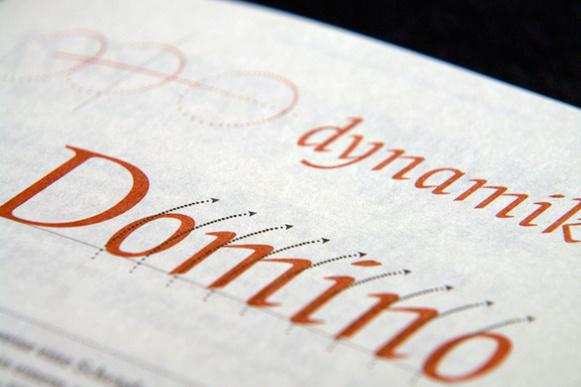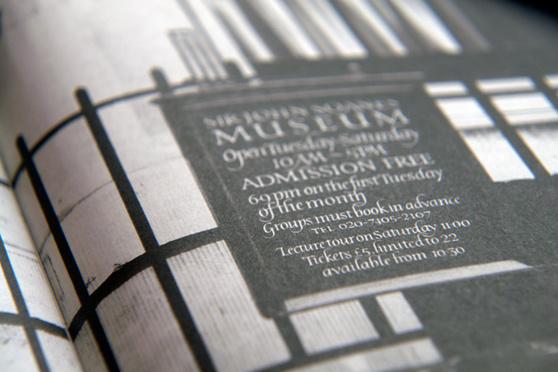
Die Typografie-Bücher aus dem »Niggli Verlag« sind nicht selten Abschlussarbeiten von Hochschulen. Einerseits ist es natürlich löblich, dass der Verlag Werke einer breiten Masse zugänglich macht, die sonst womöglich unbesehen in Universitätsarchiven verstauben würden. Andererseits macht ein erfolgreicher Abschluss nicht jede Arbeit gleichsam zu einem empfehlenswerten Buch. Als Beispiel sei hier das im letzten Jahr im gleichen Verlag erschienene Buch Bleiwüste genannt, das wohl offenbar ohne jegliche fachliche Korrektur in den Druck ging und entsprechend schlechte Bewertungen erhielt.
Insofern war ich auch bei dem neuen Buch »Kursiv – Was die Typografie auszeichnet« etwas skeptisch, denn auch hier handelt es sich wieder um eine Diplom-Abschlussarbeit, diesmal von Hendrik Weber an der Hochschule für Grafik und Buchkunst Leipzig.
Die zweifarbig gesetzte Broschur gefällt mir ihrer sachlichen und unaufdringlichen Gestaltung. Die angenehm lesbare Fließtextschrift Lirico geht ebenfalls auf das Konto des Autors.
Das Buch gliedert sich in drei Teile. In der Einleitung geht der Autor dem Zweck und der Definition des Begriffes auf den Grund. Denn so gewöhnlich uns der Begriff auch erscheint, so schwierig gestaltet es sich doch, ihn exakt zu definieren. Der zweite und größte Teil des Buches widmet sich der Geschichte der kursiven Schrift. Auf ca. 40 Seiten wird die über 2000-jährige Geschichte fundiert und reich bebildert dargestellt. Löblich sind hier auch die Umfangreichen Quellenangaben, die im Rahmen einer solchen Arbeit nicht immer selbstverständlich sind. Der abschließende Teil des Buches widmet sich schließlich dem typischen Formaufbau der Kursiven. Er beschreibt wie Schreibwerkzeug und Schreibstil den Duktus und den Charakter der Kursiven prägen und wie sich dies auf den Buchstabenaufbau der Klein- und Großbuchstaben auswirkt.
Das Buch ist perfekt für echte »Typomanen« denen kein noch so kleines typografisches Detail uninteressant erscheint. Entsprechende Begeisterung sollte man aber auch schon mitbringen, um das Buch genießen zu können. Für Einsteiger ist es wahrscheinlich etwas zu speziell und detailverliebt.
Untertitel: Was Typografie auszeichnet